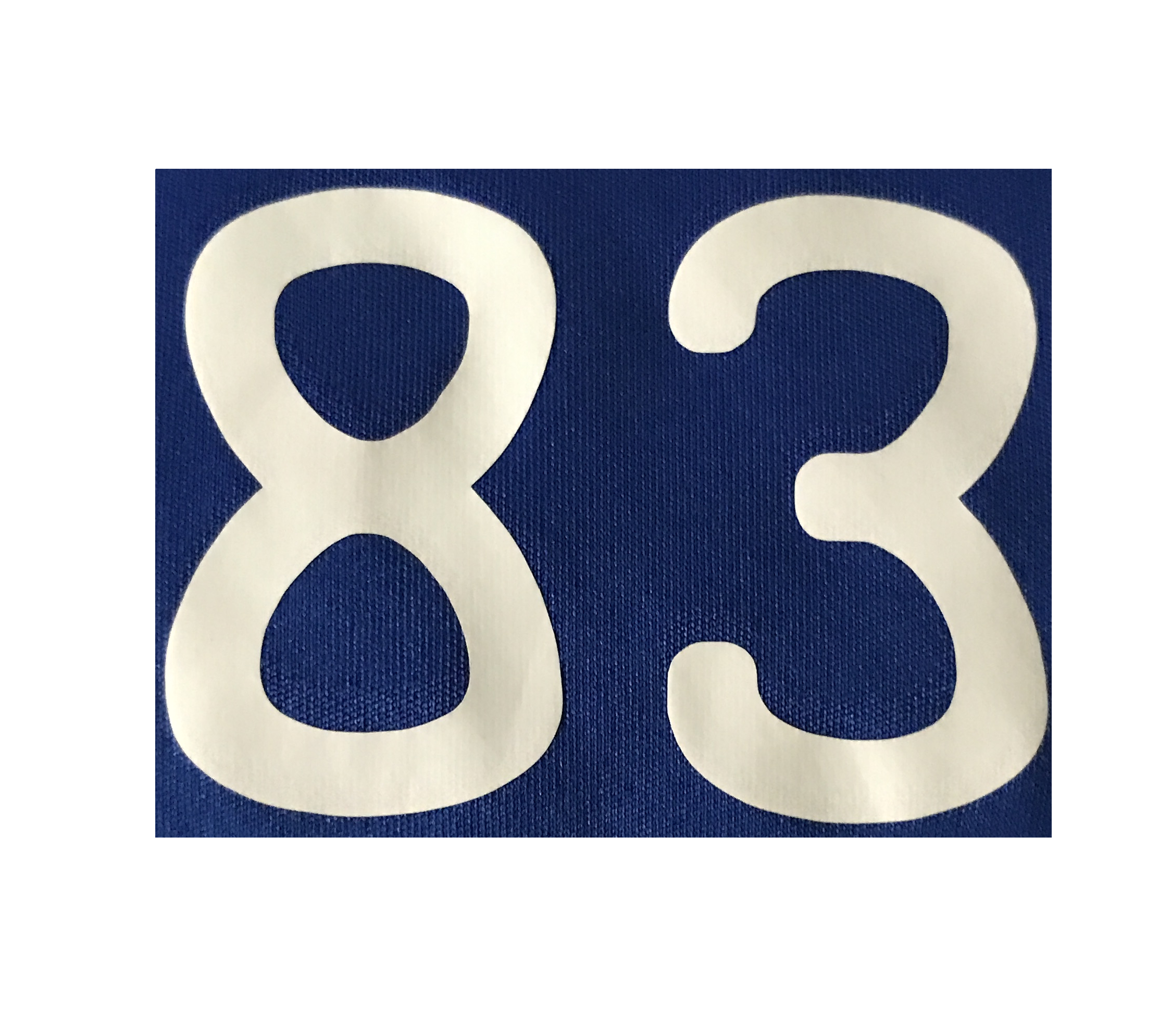
Suche Schriftart (Adidas-Trikot)
Woher stammt das?
Sporttrikot-Rückennummer?
Wenn ja, welcher Sportkleidungs-Hersteller?
Wir hatten solche anfragen schon öfter, und dabei zeigt sich, das sich die großen Sprortbekleidungshersteller für jede Saison ganz spezielle Schriften gestalten lassen, die dann bei Sportvereinen, oder auch nationalen Sportverbänden für ihre Mannschaften gewählt werden, und so eben auch zur Entscheidung beitragen, für welchen Sportkleidungs-Hersteller als offiziellen Ausstatter man sich entscheidet, was natürlich über die Fankleidung ein Millionengeschäft ist.
Diese Schriften sind dann zumeist nicht erhältlich, und die ausgeplotteten Ziffern und Buchstabensätze muss dann der Zeugwart vom jeweiligen Hersteller fertig bestellen, um das dann nur auf die Trikots zu bügeln
Das sind von T-shirts wo die Nummern vorne in klein drauf sind. Es ist zwar Adidas aber wurde von ein Sportladen bedruckt der leider zu gemacht hat. Daher kann ich diesen nicht mehr fragen und suche schon die ganze Zeit im Internet nach dieser Schriftart.
Die Artikel sind zwar von Adidas aber wie geschrieben wurden diese von einen ehemaligen ortsansässigen Sportladen bedruckt.
Bei diesem Font handelt es sich nicht um den Originalfont von Adidas, sondern um eine, zugegebener weise gut nach gezeichnete          Version. Der Copyright-Eintrag beweist dies:
Vectorized by Azmie (switchimageproject), requested by Abdul, fonted by Character
Dere Markeneintrag für die Schriftart "Adidas Unity" ist laut DPMA gelöscht (da stehr "Alte vernichtet"), nichts desto trotz könnte man im Namensbestandteil einen Verstoß gegen die Wortmarke Adidas sehen. So gesehen etwas zweifelhaft. Azmie hätte wohl besser dran getan, sie Unity-Trikot zu nennen, zum Beispiel.
switchimageproject ist übrigens eine Seite, die sich auf solchen Nachbau von Trikot-Fonts und Symbolen spezialisiert hat, also auch die jeweils aktuellen Zeichensätze sehr bald anbietet, und so zum Nachbau von Fan-Trikots sorgt. Ähm... Grauzone? Wohl eher dunkelgrau.